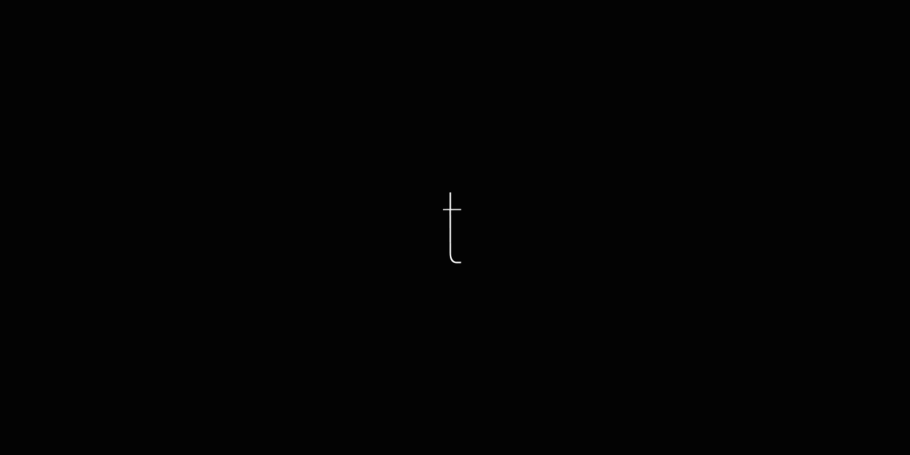
Helvetica® Now Variable.
KMS x polices variables.
Leading brand consultancy KMS recently deployed our newest Variable release, Helvetica Now Variable, in a redesign of its website.
The verdict? It’s “a new and powerful instrument for creating on-brand touchpoints. This will definitely change the role typography can play in design systems.”
“ As a technology-driven design firm, adopting disruptive technologies is a part of our DNA. From virtual and augmented reality to parametric modelling to robotic process automation and more, we see the adoption of Variable fonts – itself a disruptor – as no less an opportunity to enhance, differentiate, and digitally optimize IBI Group’s brand identity. ”
Variable in the real world.
Wie befolge ich meine Markenrichtlinien, wenn ein variabler Font so viel mehr Optionen enthält als ein herkömmlicher Font?
Sie können einen variablen Font genauso verwenden wie einen herkömmlichen Font. Variable Fonts bieten eine Vielzahl von Stilen, die wie Koordinaten in einem Diagramm gemessen werden. Die Fonts enthalten jedoch vorausgewählte Koordinaten, die wie herkömmliche Fonts benannt sind: normal, fett usw.
Sie haben zwei Möglichkeiten, einen variablen Font in einem Designprogramm zu verwenden: Sie können über das Fontstil-Menü einen Stil aus Ihren Favoriten auswählen, ebenso wie Ihre anderen Fonts. Alternativ können Sie eine beliebige Koordinate eingeben, in der Regel mit einem Schieberegler.
Wenn Ihre Markenrichtlinien also Helvetica Now Standard erfordern, können Sie ganz leicht darauf zugreifen. Aber wenn Sie die Breite etwas anpassen möchten, ist auch das kein Problem.
Wie sieht es mit den Kosten aus? Kaufe ich nicht lauter Stärken und Stile, die ich gerade gar nicht brauche?
Möglicherweise! Aber hier ist das Wort „gerade“ entscheidend.
Ein variabler Font bietet eine umfassende Palette an Ausdrucksmöglichkeiten. Er umfasst die spezifischen Stärken und Stile, die Sie gerade benötigen, aber bietet Ihrer Marke zusätzlich die Flexibilität, sich in Zukunft weiterzuentwickeln und zu experimentieren. Für Marken, die eine Schrift wirklich nur in einer einzigen Stärke benötigen, ist ein variabler Font möglicherweise nicht sinnvoll. Doch für Marken, die mehrere Stärken einer Schrift verwenden oder ihre Verwendung einer bestimmten Fontfamilie erweitern möchten, bieten variable Fonts unglaubliche Vorteile gegenüber dem ständigen Kauf statischer Fonts.
Kann ich einen variablen Font unterteilen, um die Dateigröße zu reduzieren?
Auf jeden Fall. Variable Fonts beinhalten eine ganze Menge an Daten, daher ist die Datei größer als eine einzelne statische Fontdatei. Wenn Sie einen variablen Font von Monotype erwerben, können wir mit Ihnen zusammenarbeiten, um die Datei nach Ihren spezifischen Anforderungen zu unterteilen.
Aber wenn die Dateien variabler Fonts größer sind, wie können sie dann die Seitenladezeiten verbessern?
Es stimmt, dass Dateien variabler Fonts größer sind als eine einzelne statische Fontdatei. Doch ein variabler Font ist in der Regel kleiner als zwei oder drei statische Fontdateien zusammengenommen. Wenn Ihre Website also mehrere Fonts verwendet und daher mehrere Fontdateien heruntergeladen werden müssen, führt der Umstieg auf einen variablen Font zu schnelleren Ladezeiten und einer besseren Leistung.
Ein variabler Font erreicht also in der Regel einen Bruchteil der Größe der statischen Fonts, die er ersetzen kann. So entspricht beispielsweise jede Desktop-Fontdatei von Helvetica Now Variable ungefähr 12,5 % der Größe der 72 statischen Fonts, die hierdurch dargestellt werden können.
Funktionieren variable Fonts in allen Browsern, E-Mail-Clients und anderen Touchpoints?
Ja und variable Fonts sind auf dem besten Weg, zum Branchenstandard zu werden. Alle gängigen Webbrowser unterstützen mittlerweile variable Fonts, Apple stellt seine Systemfonts bereits in variabler Form bereit, Microsoft plant wichtige Updates für die Office-Suite, um variable Fonts zu unterstützen, und immer mehr Adobe-Apps integrieren die Unterstützung von variablen Fonts.
Variable Fonts sind also nicht nur ein kurzer Trend, sondern ein neuer Standard.